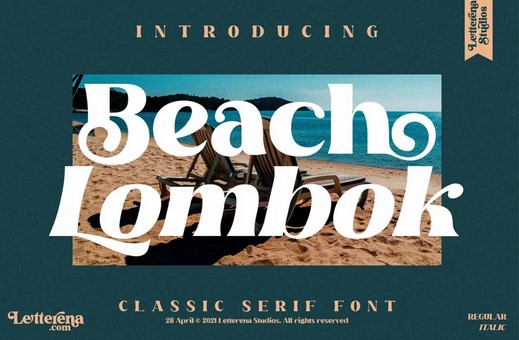
[Fontbundles] Beach Lombok - Luxury Serif Font
Beach Lombok - Luxury Serif Font, от Letterena, это шрифт с засечками, подходящий для любых проектов, таких как: логотипы, брендинговые проекты, дизайн домашней одежды, упаковка продуктов, кружки, цитаты, плакаты, сумки, футболки, обложки книг, именные открытки, пригласительные билеты, поздравительные открытки, этикетки, фотографии, водяные знаки, специальные мероприятия, и все другие роскошные и красивые проекты, которым нужен вкус Luxury Serif.